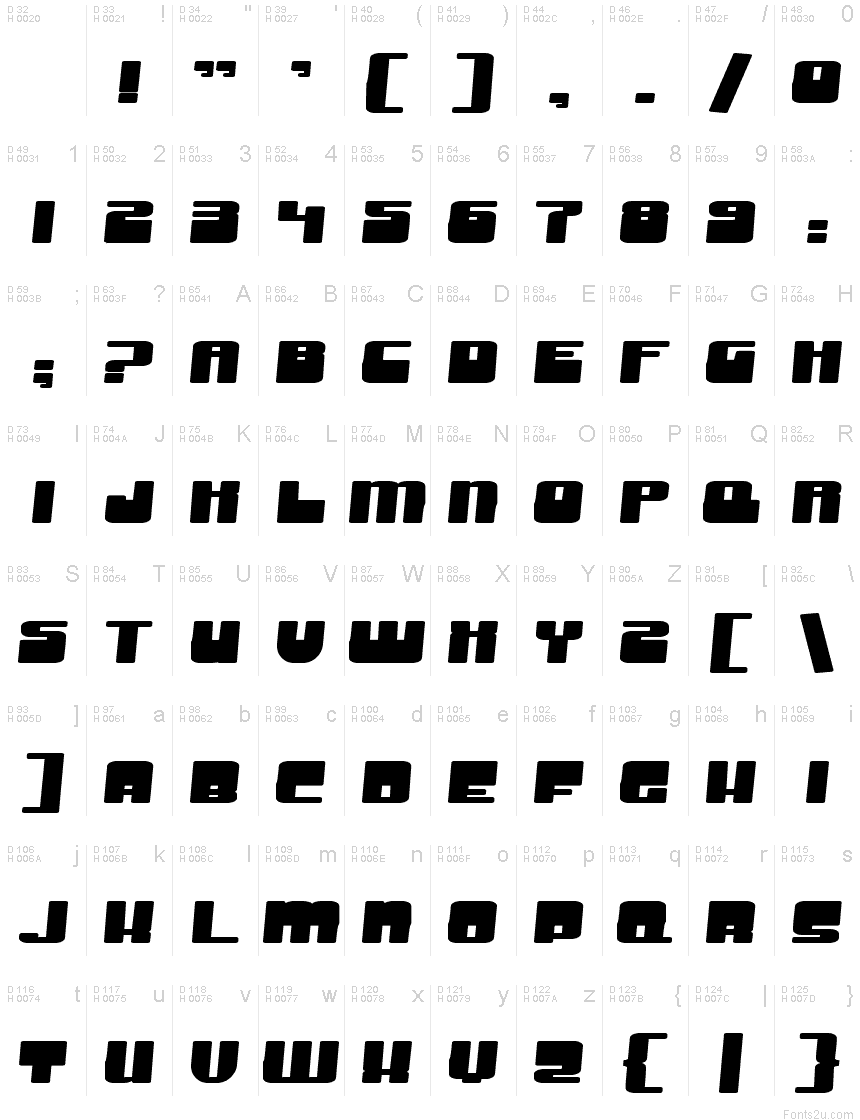
Groove Machine Expanded Bold od Shywedge to darmowy, groovowy krój pisma typu display, który uderza z siłą basowego dropu. Jego masywne, rozciągnięte litery zdają się być w ciągłym ruchu, a gładkie krzywe i kanciaste światła wewnątrz liter przenoszą w klimat klubowych ulotek czy automatów do gier z lat 90. Dzięki ciasnemu kerningowi i pochylonemu rytmowi, Twoje napisy zyskują głośny, pulsujący charakter – sprawiając, że nawet krótkie słowa wyglądają jak logo.
Wykorzystaj Groove Machine Expanded Bold, aby podkręcić energię na plakatach muzycznych, okładkach albumów czy mixtape'ów, ulotkach klubowych, projektach w stylu retro, tytułach gier czy wyrazistych miniaturkach na YouTube. Ten darmowy font najlepiej prezentuje się w dużych rozmiarach, gdzie jego grube, wyraziste kształty wypełniają cały kadr. W tekstach towarzyszących zestaw go z czystym, wąskim krojem bezszeryfowym, aby nagłówek skradł całą uwagę.